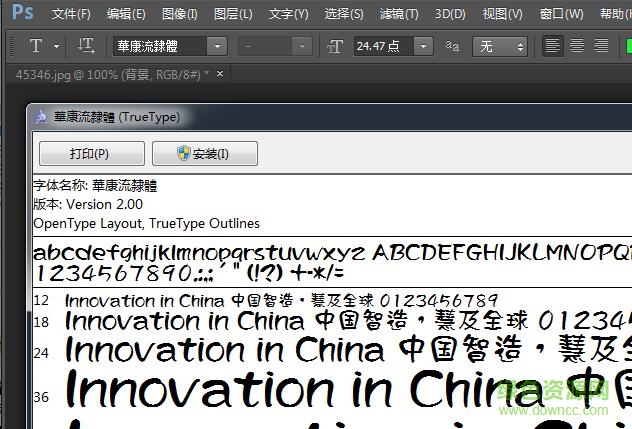
華康流隸體繁體是一款為你在美術創(chuàng)作中進行文字編輯與添加的字體樣式文件,是一款由臺灣出品的字體,能夠運用到視頻字幕制作,海報制作,以及眾多生活文字編輯當中,用途廣泛!
4.華康流隸體繁體可以適用于名片設計、平面設計、廣告設計、報紙雜志、企業(yè)LOGO、商標注冊、電視臺廣告等領域,有喜歡的網(wǎng)友可免費下載收藏。